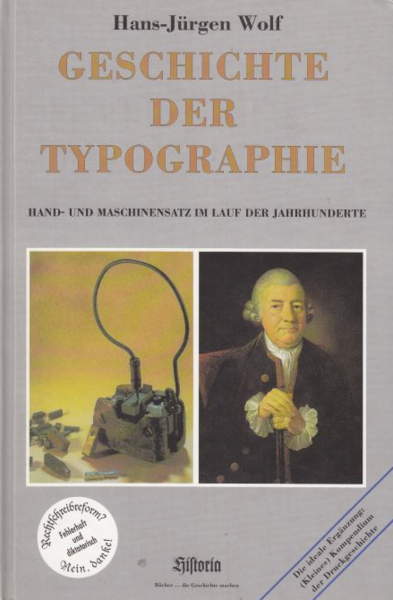
Geschichte der Typographie
Eine illustrierte Geschichte der Typografie, die alle technischen und künstlerischen Verfahren des Druckwesens erschöpfend behandelt.
Rezension
Wie man alte Bücher neu macht.
von Martin Z. Schröder
Der Historiker Hans-Jürgen Wolf hat es zu einem gewissen Ruf gebracht. Soeben erschien seine „Geschichte der Typographie“ als erster Band eines „vierbändigen Kompendiums zur Geschichte des graphischen Gewerbes“. Hans-Jürgen Wolf ist einer der fleißigsten Geschichtsforscher überhaupt. Im letzten Jahr publizierte er die Werke „Geschichte der Hexenprozesse“, „Geschichte des Okkultismus“, „Geschichte der Prostitution“ sowie die Bücher „Sünden der Kirche“ und „Aufstieg und Untergang einer Weltreligion“. Der Mann ist fleißig wie ein Bienchen. Bereits 1997 gab es von ihm eine „Geschichte der Feuerwehr“ und die „Geschichte der Druckverfahren“ – huch! Sollte jene „Geschichte der Druckverfahren“ nicht Band II des „Kompendiums zur Geschichte des graphischen Gewerbes“ werden, in deren Rahmen für das Jahr 2002 als vierter Band die „Geschichte des Papiers“ angekündigt ist? Vorbestellungen nimmt der Internet-Buchhändler BOL bereits entgegen.
Ein gewisser Ernst Völker bescheinigt indes in einem der diversen Grußworte zum neuen Buch dem Autor, „die große Geschichte der Typographie, der Druckverfahren, der Buchdruckerkunst und des Papiers detailliert geschrieben zu haben.“ Der ältere Herr auf dem Foto trägt klassisches Streifenhemd und Krawatte und guckt betont seriös, nur hat er das Vorwort zur Neuerscheinung des eben edierten ersten Bandes sowie des für 2002 geplanten schon am 10. Oktober 1997 geschrieben.
Ob der Verlag eine Erklärung für das Tohuwabohu hat? Außer einer Postfachnummer in Weißenhorn bei Ulm gibt es aber keine Hinweise auf den Historia-Verlag Ulm-Wiblingen. Auch die Telefonauskunft kennt weder in Ulm noch um Ulm und um Ulm herum einen solchen. Hm. Der Grossist muß es wissen. Der hat tatsächlich eine Telefonnummer von Herrn Hans-Jürgen Wolf, dem Eigentümer des Historia-Verlages übrigens. Er wisse aber nicht, ob diese freigeschaltet, sie sei neu. Er habe überdies läuten gehört, daß der Herr Wolf im Krankenhaus liege. Die Telefonnummer funktioniert, allerdings gehört sie zu einer genervten Dame, die kühn behauptet, nicht zum erstenmal zu erklären, kein Verlag und schon gar nicht Herr Wolf zu sein. Das kann ja jeder sagen!
Eine gut informierte Buchhändlerin des Künstlerbedarfsgroßhändlers Boesner weiß näheres über ein Werk des Historia-Verlages: „Geschichte der Druckverfahren? Haben wir im Ramschangebot.“ Band II des Kompendiums, dessen angeblich erster Band als taufrisch auf den Rezensententisch gelangte, ist nämlich im Jahr 1992 schon einmal erschienen und war bis zum Dezember 1996 für 98,00 DM im Buchhandel zu haben. Das Antiquariat der Schweizer Schibli-Doppler AG empfiehlt seinen Buchhändlern seither unverbindlich einen Ladenverkaufspreis von 49,95 DM. Dasselbe Buch bietet BOL als 1997 erschienen für 78,00 DM an.
Wenn das „neue“ Buch etwas taugte, nähme man Hans-Jürgen Wolf seinen komischen Versuch, Leser und Kritiker mit getürkten Neuerscheinungen von Ramschware aufs Kreuz zu legen, vielleicht nicht krumm. Aber diesem Werk ist bereits seinem mit werbenden Buttons und Streifchen versehenen Einband anzusehen, daß weder Autor noch Verlag, was ja hier keinen Unterschied macht, auch nur einen Schimmer von Typographie haben. Texte und Bilder sind wahl- und systemlos durcheinandergewürfelt, manche Kapitel enden mitten im Satz, auf einem Druckbogen fehlen zwei Farben, die letzten Seiten sind mit Werbeanzeigen der graphischen Industrie vollgestopft. Von Ausstattung in typographischem Sinne kann nicht die Rede sein, der Satzspiegel wurde hingeschlunzt, die Laufweite der Satzschrift wechselt nach Belieben, der Text ist fehlerhaft. Insgesamt ist dieses Werk sowohl äußerlich als auch in Text und Bild derart lausig, daß man es nicht rezensieren kann. Den so prächtige Gruß- und Lobesworte verfassenden Professoren aus Hannover und Wuppertal wie auch dem Vorstandsvorsitzenden der Druckmaschinenwerke Koenig & Bauer-Albert und dem Geschäftsführer der Voight Sulzer Papiertechnik hat die Eitelkeit mächtig mitgespielt.
Übrigens ist das Buch in einer vierfarbigen Widmung auf dem Schmutztitel einer gewissen „Bruni in Dankbarkeit zugeeignet“, während der Haupttitel einfarbig schwarz und ohne Vakatseite oder gar Frontispiz auskommen muß. Ob Bruni weiß, auf welcher Station welchen Krankenhauses Hans-Jürgen liegt? Bestimmt schreibt er dort die mehrbändige „Geschichte der Heilverfahren“ und sammelt Grußworte von Ärzten.
Untertitel: Hand- und Maschinensatz im Lauf der Jahrhunderte